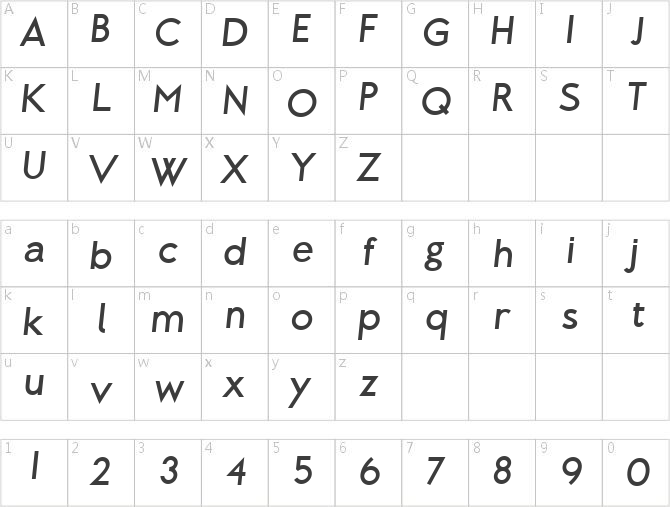
字体名称: Brixton
Brixton Bold Oblique
Brixton Bold Oblique介绍
Brixton Bold Oblique字体字库是一款让人赏心悦目、百看不厌的英文字体,适合各类广告和产品包装设计应用,字体大小0.04MB,格式为ttf字体,上传用户是shiqiuping,作者/版权方为未知